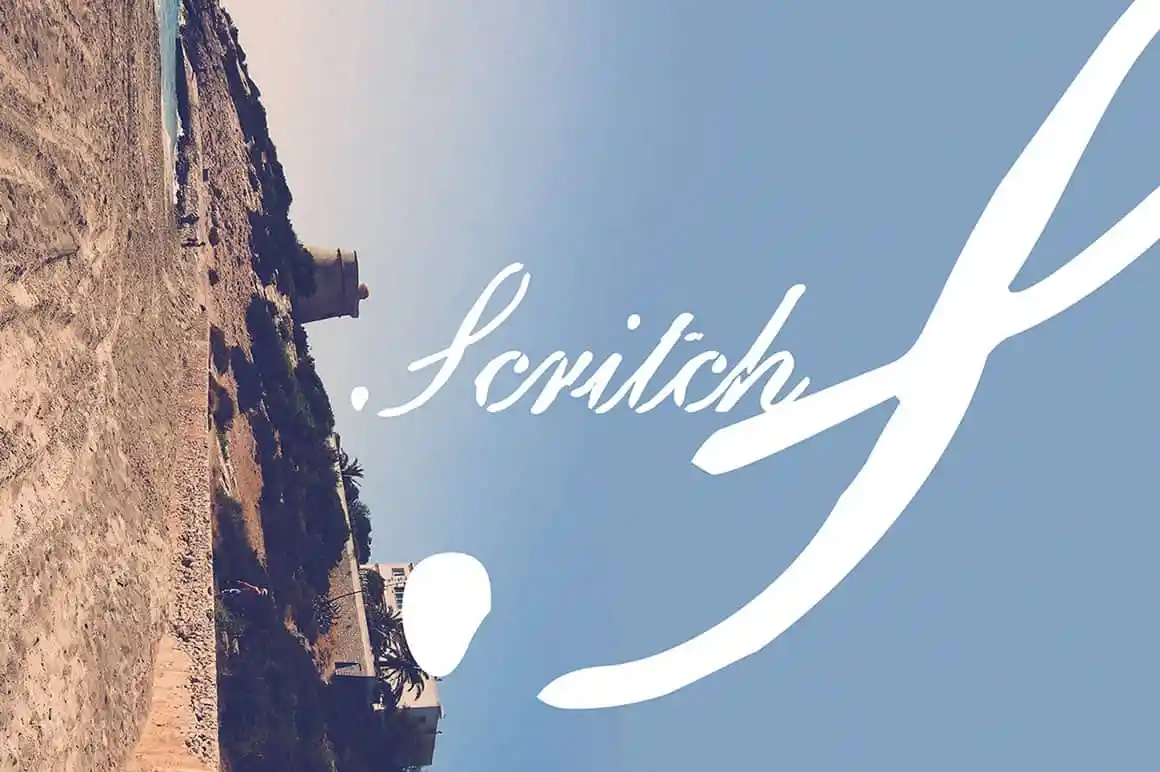
A fonte ‘Scritch Font’ é uma escolha ideal para projetos criativos, apresentando um estilo único e despojado que se destaca no mercado dos fonts customizados. Desenvolvida pelo designer Hamilton, esta font oferece a autenticidade de uma escrita à mão em seu próprio gênero grunge. Suas linhas sutis e textura única permitem que o seu texto ganhe um tom único sem perder sua clareza e legibilidade. Este é perfeito para aqueles projetos onde você quer adicionar um toque distintivo, seja em design gráfico, editorial ou até mesmo em produção de mídia social, fazendo a sua fonte de escrita à mão uma opção confiável e estilosa. Descarregue já, experimente e sinta-se renovado!